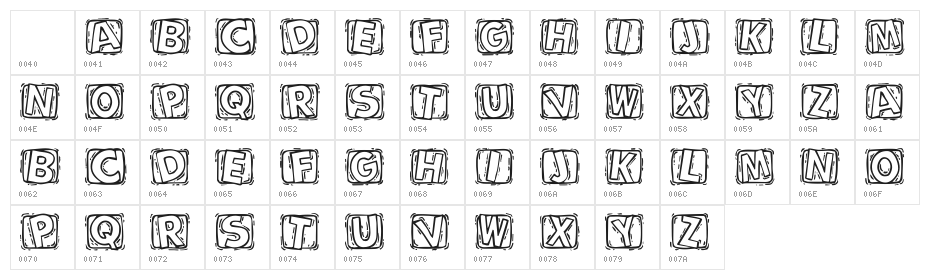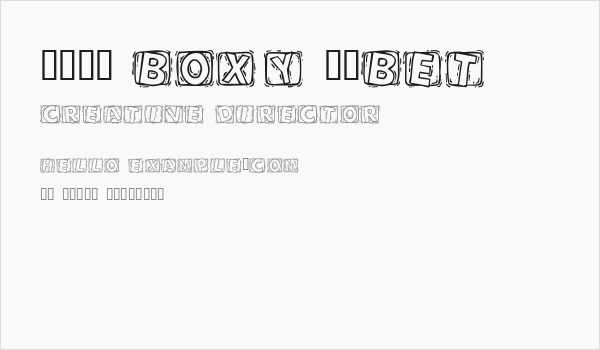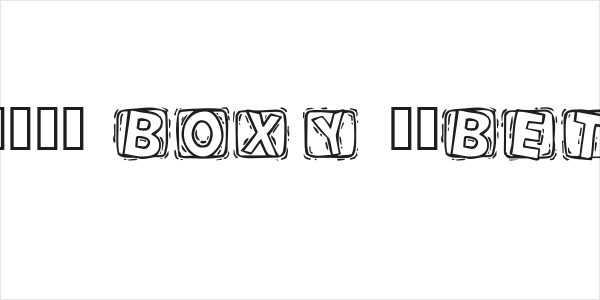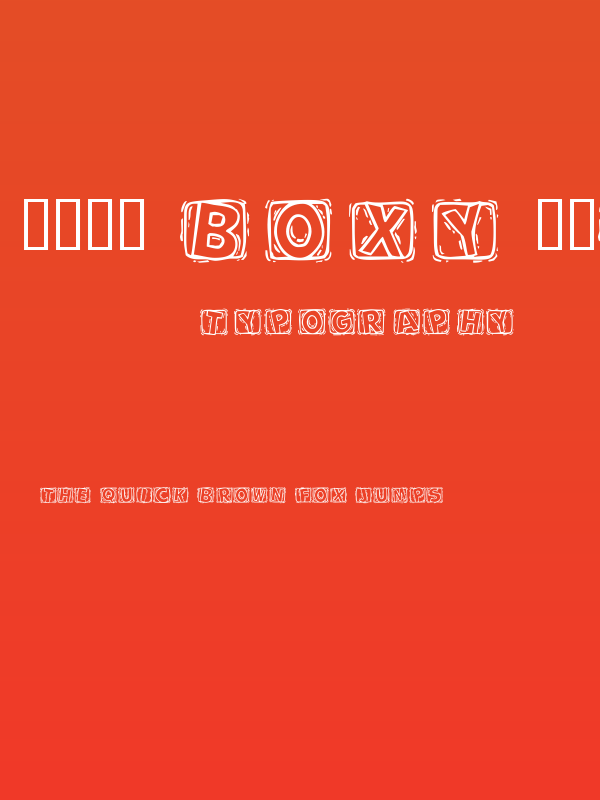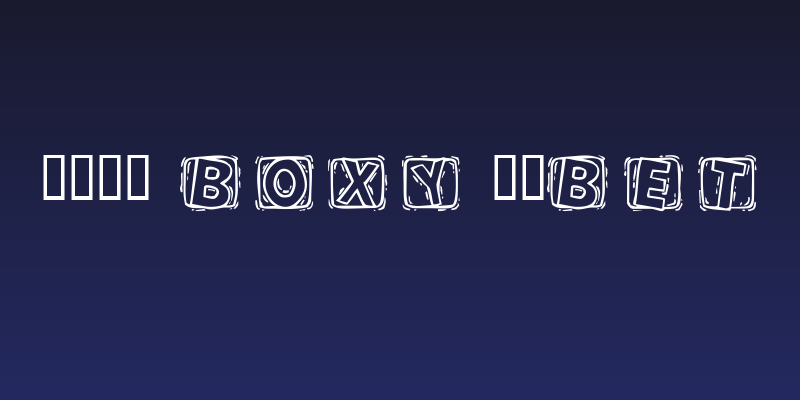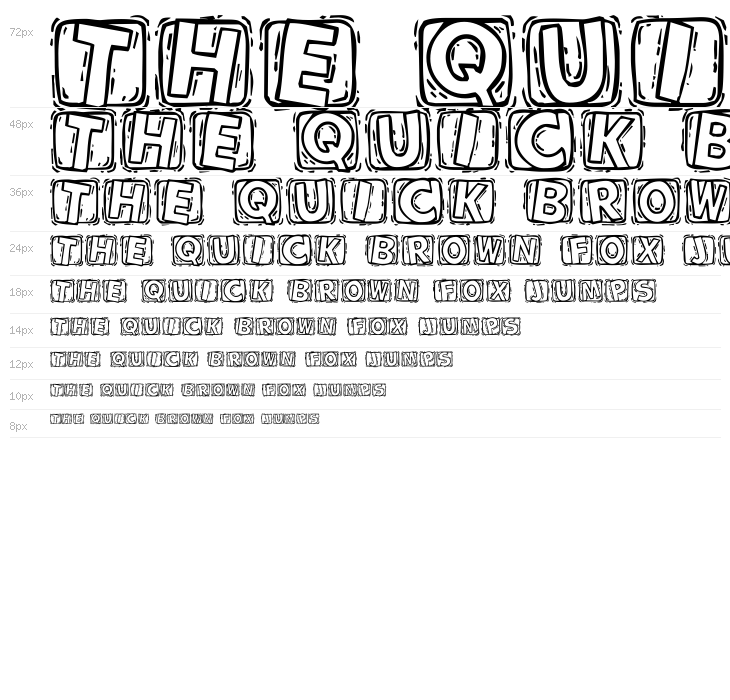
101! BoXY 'Bet Font
✎ Cartoon
| Stile generale | Playful, Artistic |
| Progetti proposti | Ideal for children's books, comic strips, playful branding, and creative posters. |